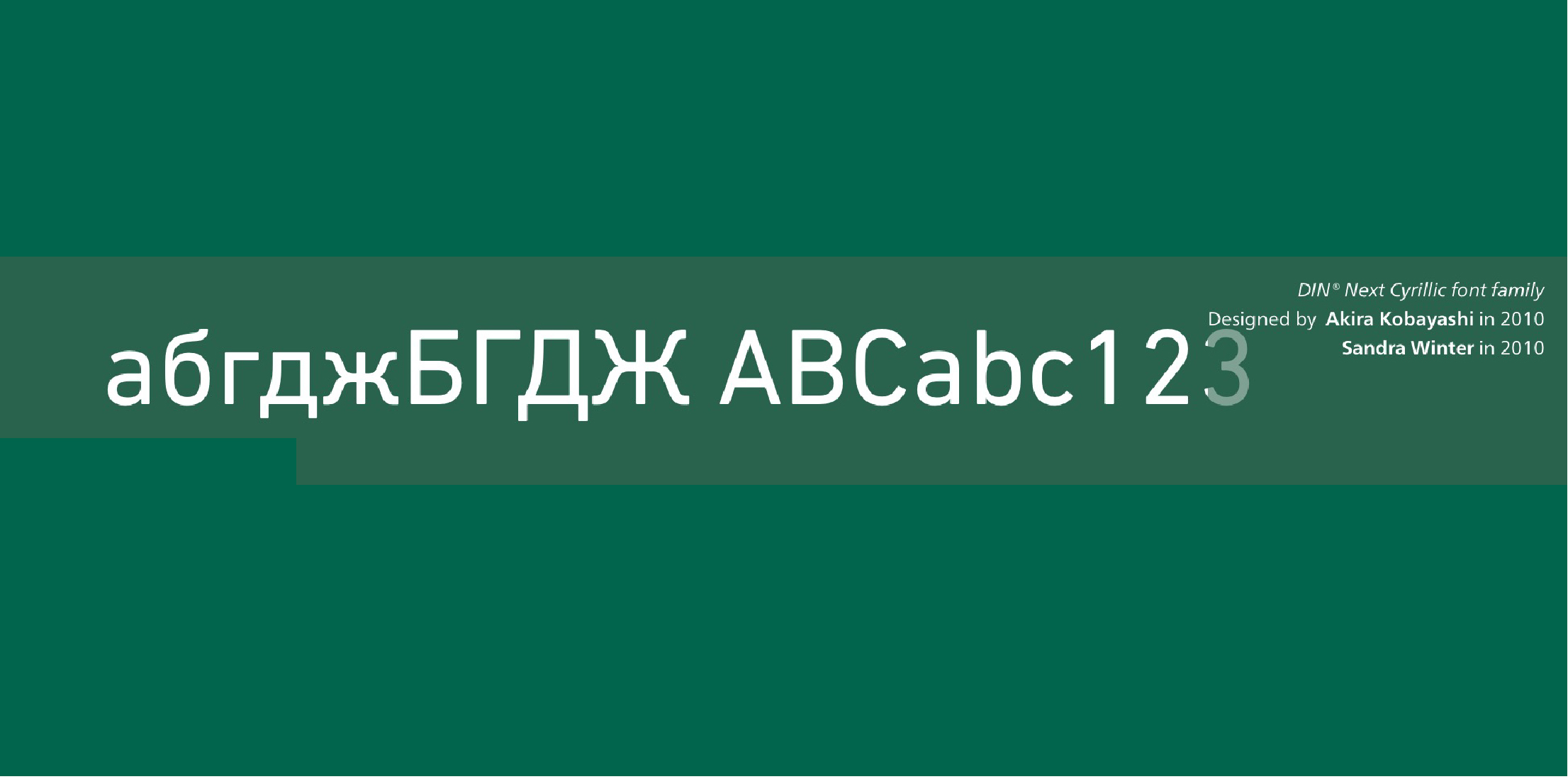
DIN® Next Cyrillic
字体品牌: Monotype 设计师:Kobayashi,Akira,Winter,Sandra 字体分类:无衬线体 字体属性:外文 字符集:Unicode 发布时间: 2010
DIN Next是一个字体系列,灵感来自经典的德国工业工程设计,具有七个字重。每种字重都配有常规、斜体和窄体,使 DIN Next 系列中的字体总数达到 21 种。
自1980年以来,Linotype一直为客户提供两种DIN 1451字体。最近更受欢迎,设计师经常要求额外的字重。
缩写“DIN”代表“Deutsches Institut für Normung e.V.”,即德国工业标准化研究所。1936年,德国标准委员会决定将DIN 1451作为技术,交通,管理和商业领域的标准字体。该设计将用于德国街道标志和门牌号。无衬线会更清晰,更直接,更容易复制。德国标准委员会不打算将设计用于广告和其他以艺术为导向的目的。然而,由于DIN 1451在德国各地的城镇名称和交通方向标志上都可以看到,因此广为人知,成为了平面设计师和广告艺术总监的选择。DIN 1451的数字版本将继续被其他国家的设计师采用和使用,巩固了其在全球的设计声誉。与 DIN 1451 原始版本相比,DIN Next 的字母存在许多细微的差异。这些是由小林添加的,以使新的字族在21世纪的媒体中能发挥更多作用。例如,尽管 DIN 1451 的角都是尖角,但 DIN Next 都略微圆润。
Linotype 的 DIN 1451 Engschrift 和 Mittelschrift 已通过德国 DIN 研究所的认证,可用于官方标牌项目。DIN Next可用于任何其他项目和任何其他国家的工业标牌!DIN Next专为平面设计师量身定制。
DIN Next系列已经扩展了七个阿拉伯字重和五个梵文字重。网站上显示的梵文字体不会显示字体的所有功能,因此并非所有语言功能都可以正确显示。